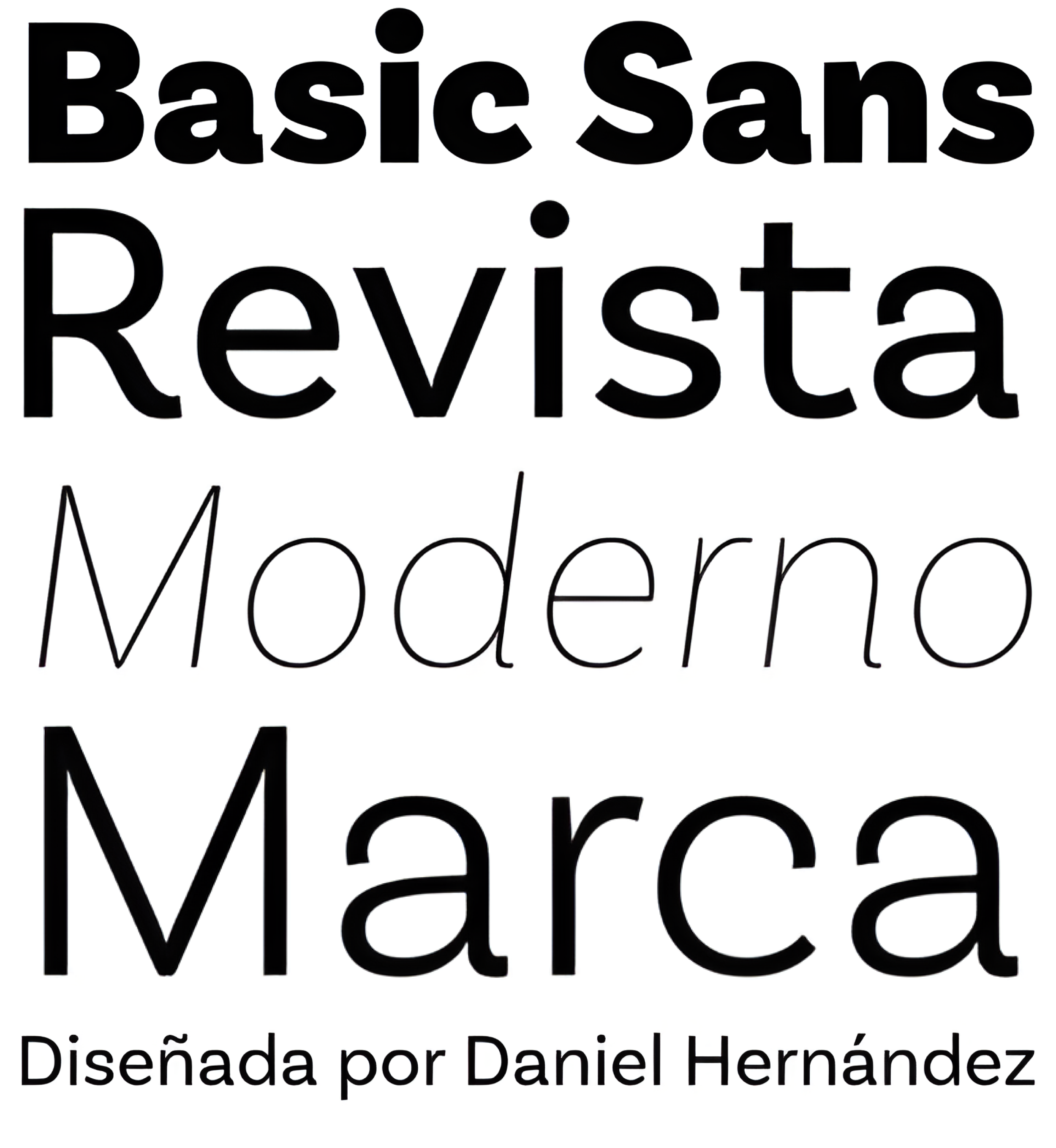
| Año | 2016 |
| Créditos | Daniel Hernández |
| Descripción | Sans básica: Una sans necesaria. Diseñada por Daniel Hernández Una familia de rasgos grotescos con un estilo funcional, neutro y aparentemente limpio que busca mantener una apariencia neutra (o básica) sobre el papel, pero incluyendo muchos detalles que le dan una personalidad única. Basic Sans es una tipografía sans-serif muy adecuada para proyectos editoriales, textos de tamaño medio, branding, carteles, titulares y ¡mucho más! Esta familia tipográfica está disponible en 7 pesos -desde Thin hasta Black-, además de cursivas a juego, y cuenta con un conjunto de 416 caracteres compatibles con 206 idiomas diferentes. |
| Familia(s) | Basic Sans |
| Estilos | 28 |